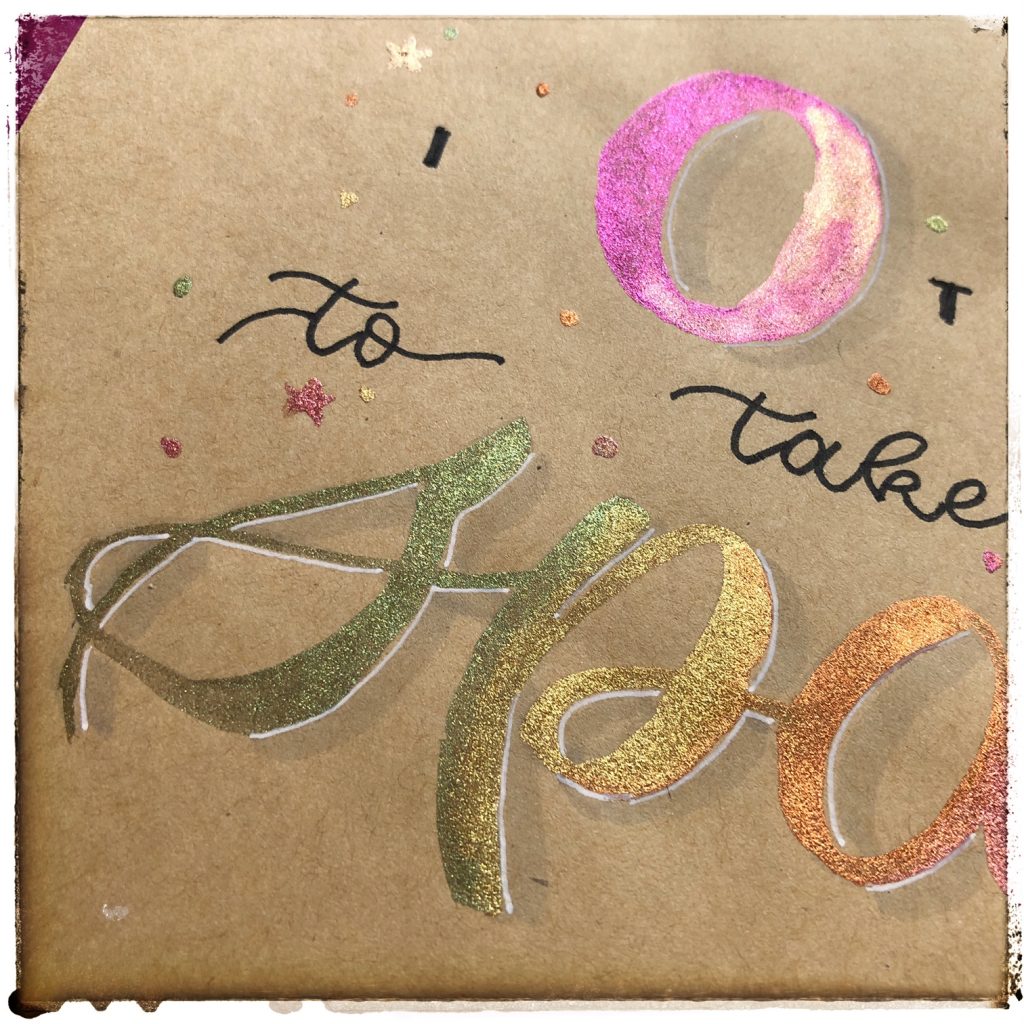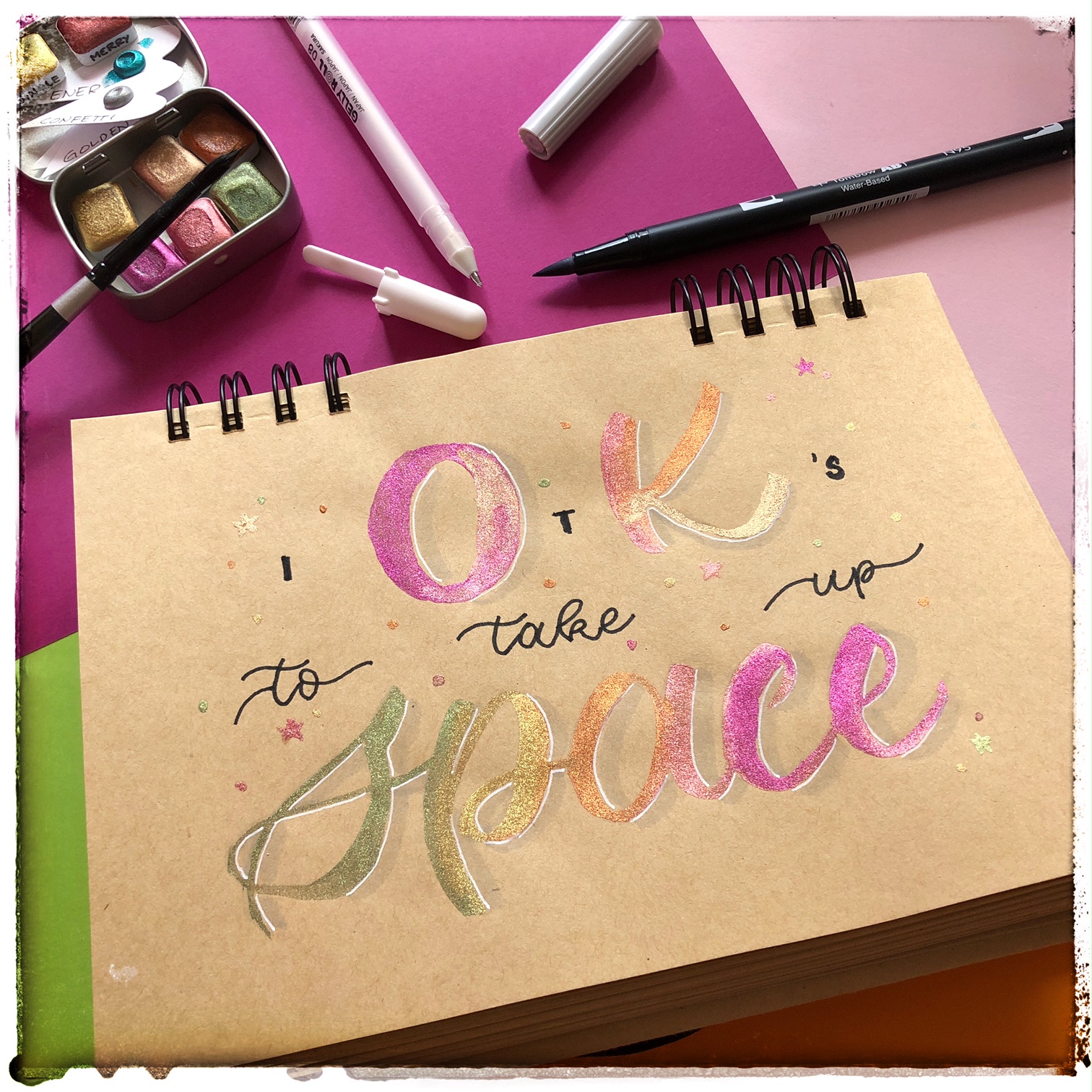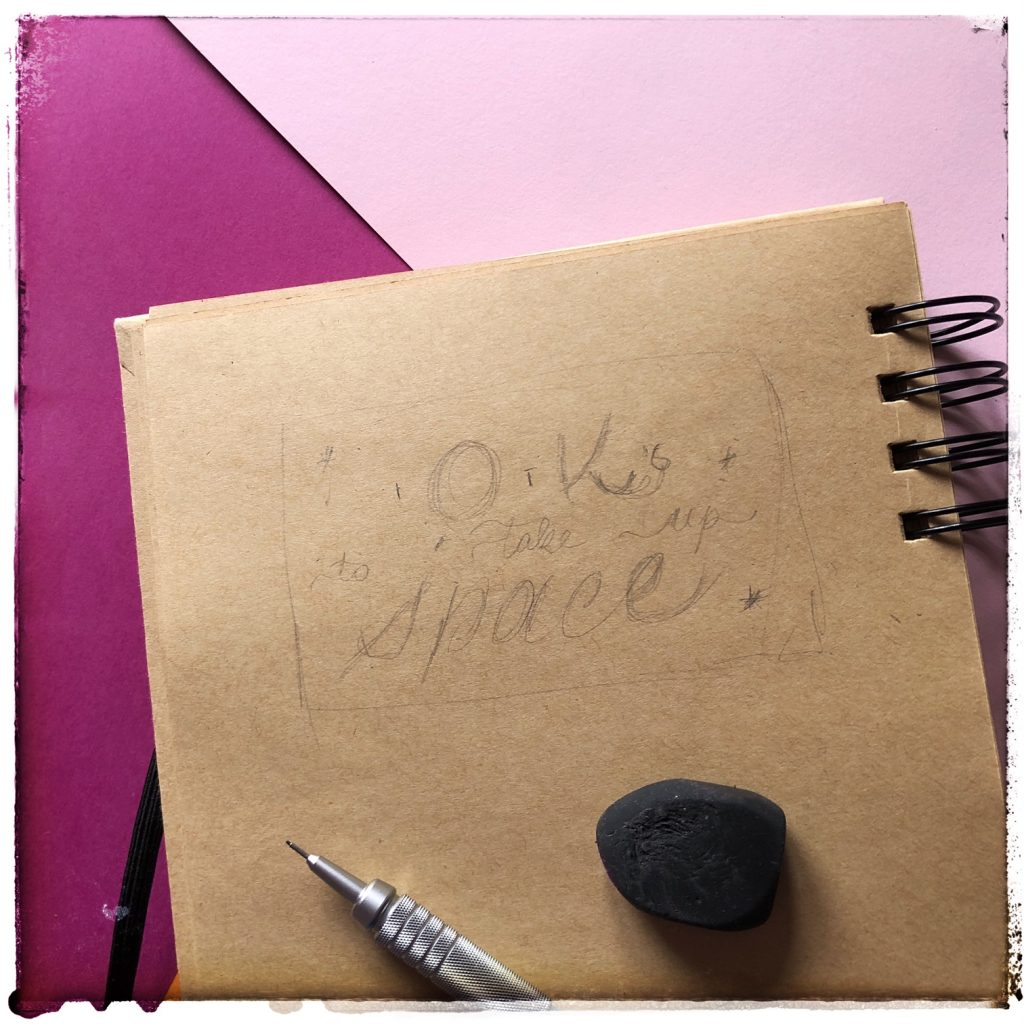
Akvarell kalligráfia
Mindennel is lehet kalligrafálni, így az akvarell festékkel is. A következő kis motivációs idézeten fogom bemutatni milyen egyszerű is ez.
akvarell kalligráfia
Az elmúlt időszakban kicsit eltűntem, sokat kellett dolgoznom és ezért kicsit háttérbe került a kalligráfia és az akvarell festés. A munka nem lett kevesebb, de szeretném folytatni a kis projekteket. Így itt is van ez a motivációs idézet – its’s ok to take up space – nézzük meg hogyan lehet kalligráfiával és akvarell festékkel feldobni. Korábban mutattam egy ecsetfilces összemosós verziót, de most megmutatom hogyan tudod használni az akvarell festéket kalligráfiára és letteringre. Az elején azt hittem, hogy ez valami varázslat, hogy valaki csak úgy neki áll festékkel kalligrafálni, persze ennek is meg van a módszere, olvass tovább és te is megtudhatod, hogy mi az!
Mi szükséges az akvarell kalligráfiához?
• kb. A5 méretű, vastagabb papír, olyan 200 g körül, hiszen akvarell festékkel dolgozunk, ami el tudja áztatni a papírt, de nem szükséges hozzá effektív akvarell papír, de ha csak az van, az is tökéletes.
• nagyon világos szürke ecsetfilc, pl.: Tombow N95
• akvarell festék, egy metálfényűt használok most, Colorsbyvita festékeit imádom, ha teheted egyet-egyet engedj meg magadnak,
• ecset, itt a méret függ a papír nagyságtól, ehhez olyan 4-es ecsetet ajánlok,
• fekete és fehér toll (lehet zselés vagy ecsetfilc),
• ceruza, radír.
Első lépés – A kompozíció
Ha egy hosszabb idézettel dolgozunk, mint ez, érdemes kiválasztani a kulcsszavakat, amelyek köré a kompozíció épül. Számomra az „OK” és a „space” szó volt, ami ebben hangsúlyos, így ezeket fogom díszíteni az akvarell festékkel. Ezután meg kell határozni a formát, amiben gondolkodsz: téglalap, kör, négyzet vagy ovális. Ezek a leggyakoribbak. Most egy egyszerű téglalapot választottam. Nem biztos, hogy elsőre jön a tuti verzió, így akár érdemes több verziót is felrajzolni. Bevallom ez elsőre tetszett, így megálltam itt.
akvarell kalligráfia kompozíció
Szóval a téglalap felső felében van az „OK” középen, míg a „space” pedig alul középen. Az „OK” olyan rövid és az „it’s” is, hogy összekombináltam őket, így az „OK” betűi elé, közé és után került az „it’s”, de jóval kisebb méretben, hiszen ez esetben ez az összekötő szöveg. A „to take up” középre került, monoline stílusban, kb. az „it’s”-szel azonos  nagyságban. A végén majd feldobjuk az egész kompozíciót néhány pötyivel és csillaggal.
Második lépés – Akvarell kalligráfia
Skicceljük fel az egészet a kívánt méretben, érdemes nagyon halványan dolgozni, nehogy átüssön az akvarell festéken. Jöhet a szürke ecsetfilc a nagyobb szavakra. Majd egész egyszerűen kezd el kifesteni a szürke vonalakat, ahol vastag, ott vastagabbra, ahol vékony, ott vékonyan. A vastagabb részeknél érdemes keverni a színeket, hogy létrejöjjön az akvarell csodája, ahogy keverednek a színek. És ennyi, ez a nagy trükk, amit használunk, ugye milyen egyszerű?
akvarell kalligráfia összemosás
Ha kifestetted a betűket, akkor jöhetnek a „töltelék” szavak. Az „it’s” kicsit vastagabb nyomtatott nagybetű, míg a „to take up to” sima monoline kalligráfia.
Második – Díszítés
Az ilyen idézeteket, kiemelt szavakat érdemes feldobni némi díszítéssel. Ezek általában az árnyékolás különböző technikái. Erről majd szintén tervben van egy poszt, hogy mit, hogyan érdemes használni.
Szóval most úgy határoztam, hogy a bal felső sarokból jön a fény, így minden jobb oldal árnyékban van. Először egy fehér tollal húztam meg a betűk jobb oldali kontúrját, majd utána újra a világos szürke ecsetfilccel húztam egy csíkot, ami így az árnyékot adja.
Ha ezzel meg vagy jöhetnek a pötyik és a csillagok. Úgy oszd el őket, hogy oda jussanak, ahol nagyobb, szabad terek maradtak. Jelen esetben a bal és jobb felső sarok, középen, kicsit a jobb sarokban is. Használd azokat a színeket, amelyeket a betűkön alkalmaztál.
És már kész is az első közös kompozíciónk!
akvarell kalligráfia